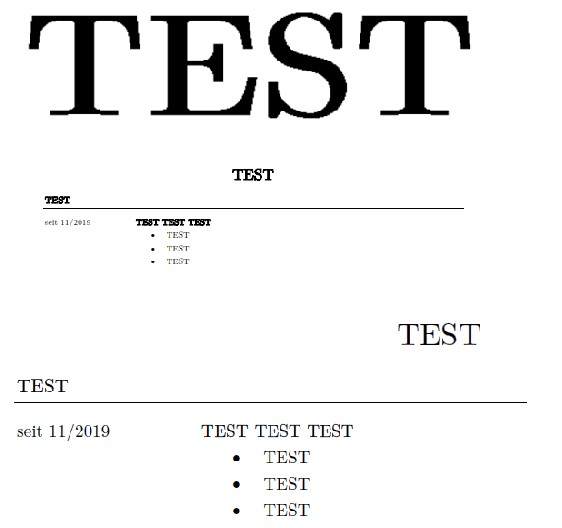
Schriftart wird in PDF weder bei drucken noch export übernommen
Word bringt mich gerade zur Verzweiflung.
Ich habe die exterene Schriftart "NewComputerModern10" (LateX Schriftart) in Word installiert. Funktioniert wunderbar - bis man das ganze als PDF möchte. Vorweg - Schriftart in die Datei einbette ist aktiviert.
Exportiere ich die Datei (oder Speicher unter... und als Dateiformat PDF), hat man beim lesen das Gefüfl, das Schriftbild ist "nicht sauber". Beim reinzoomen sieht man dann, dass das an einer "verpixelten" Qualität liegt (Ganz oben im angehangenen Bild).
Druckt man die Datei als PDF, kommt es auf das PDF Tool an:
Beim Adobe Reader wird "Fett" nicht berücksichtigt (Ganz unten im angehangenen Bild) und beim XChange Editor wird die fette Schrift "überladen" fett dargestellt (Mitte des angehangenen Bildes).
Kann man hier was machen oder kann ich mir die Schriftart abschminken?
Kann doch nicht sein, dass in Word alles Tutti angezeigt wird aber es nicht möglich ist, dies in PDF zu speichern.
Wo/wie genau hast Du die Schrift installiert?
Wenn die Schrift nicht in den Schriften des OS ist, mag Adobe die nicht. War jedenfalls so mit Adobe XI. Keine Ahnung ob sich daran was geaendert hat.
Das was bei Dir passiert scheint ein Einbetteten als Bitmap zu sein, nicht ein Einbetten als Font.
Third Party Fonts und PDF-Export sind seit 2016 ein No Go bei Office. In der Auswahl an Standardschriften sollte doch etwas vergleichbares zu dieser 08/15-Antiqua zu finden sein.
Einfach doppelklick auf OpenType Datei und dann "installieren". Habe nun noch zwei andere Schriften (TTF) mit denen es insofern schonmal besser klappt, dass beim "Druck" dies einheitlich dargestellt wird, also keine Unterschiede zwischen den PDF - Tools. Fette Schriften werden aber nur "angehaucht" dargestellt - beim export wird "fett" weiterhin gänzlich ignoriert.
Muss es denn NewComputerModern sein? Bei Word bietet es sich doch an eine vergleichebare mitgeliferte Serifenschrift zu verwenden.
Ansonsten kannst du es vielleicht mit Latin Modern Roman probieren.
"Müssen" natürlich nicht. Mir gefällt diese Schriftart doch sehr und die alternativen Serifenschriften von Word finde ich nicht so pralle. Wenn das aber nicht möglich ist, dann ist es eben so, nur hätte ich diese gern übernommen.
Den virtuellen Drucker "Microsoft Print to PDF" hast du auch schon versucht? Bei mir heißt die Schriftart(-Familie) übrigens CMU und die macht bei mir keine Probleme wenn ich die Printfunktion in Word und den besagten Drucker nutze.
Ja, mit dem Drucke ich immer meine PDFs. Wo hast du deine CMU Schriften denn her? Sonst teste ich mal deine.
Vielen Dank. Es ist besser, aber noch nicht 100%. Die fetten Buchstaben werden nur so "halb fett" dargestellt, so dass es sich zu wenig abhebt. Schade, dann werde ich wohl eine der Word Schrifte nehmen müssen...